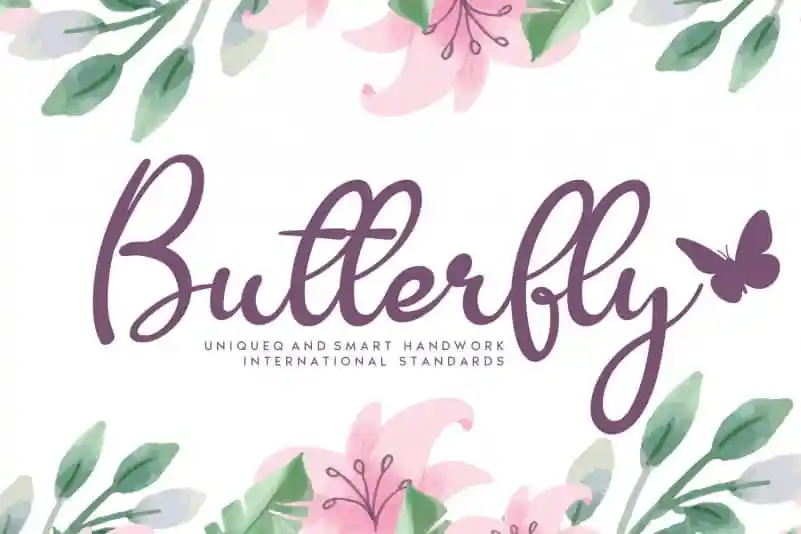
Butterfly Script Font – Download Grátis
Descubra a beleza única e autêntica do Butterfly Script Font, uma fonte escrita à mão criada pelo designer andikastudio. Este especial produto oferece uma experiência surpreendente e diversificada de design, especialmente desenvolvido para personalizar seus projetos digitais de maneira única e incrível. Com a Butterfly Script Font, você encontra um recurso versátil que pode ser utilizado em uma ampla gama de aplicações, desde websites até aplicativos móveis. Seu charme fluido e delicado combina com qualquer tipo de projeto, tornando-o ideal tanto para ambientes elegantes quanto para aqueles que buscam algo mais descontraído e criativo. Quer criar letras chamativas e interessantes, ou apenas adicionar um toque pessoal a seus projetos? A Butterfly Script Font é sua melhor opção. Não hesite em experimentar; você vai apreciar seu design único, suave e moderno. Seja para uso pessoal ou comercial, esta fonte é perfeita para qualquer projeto que deseje dar um toque distintivo e personalizado.